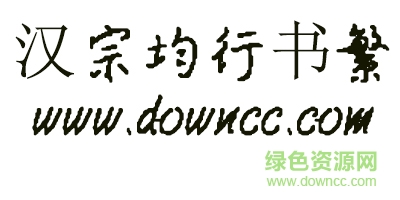
王漢宗均行書繁體風(fēng)格很獨特,是行書字體中比較突出的一款字體。在進(jìn)行ps設(shè)計、word文字排版的時候可以用得到。支持Win7、Win 8等系統(tǒng)!歡迎大家下載使用。
王漢宗均行書繁是一款王漢宗類行書字體,字體效果比較正規(guī),喜歡行書體字的朋友可以來綠色資源網(wǎng)下載使用看看效果如何。
行書是一種統(tǒng)稱,分為行楷和行草兩種。它在楷書的基礎(chǔ)上發(fā)展起源的,介于楷書、草書之間的一種字體,是為了彌補楷書的書寫速度太慢和草書的難于辨認(rèn)而產(chǎn)生的?!靶小笔恰靶凶摺钡囊馑?,因此它不像草書那樣潦草,也不像楷書那樣端正。實質(zhì)上它是楷書的草化或草書的楷化??ǘ嘤诓莘ǖ慕小靶锌?,草法多于楷法的叫“行草”。行書實用性和藝術(shù)性皆高,而楷書是文字符號,實用性高且見功夫;相比較而言,草書則是藝術(shù)性高,但是實用性顯得相對不足。